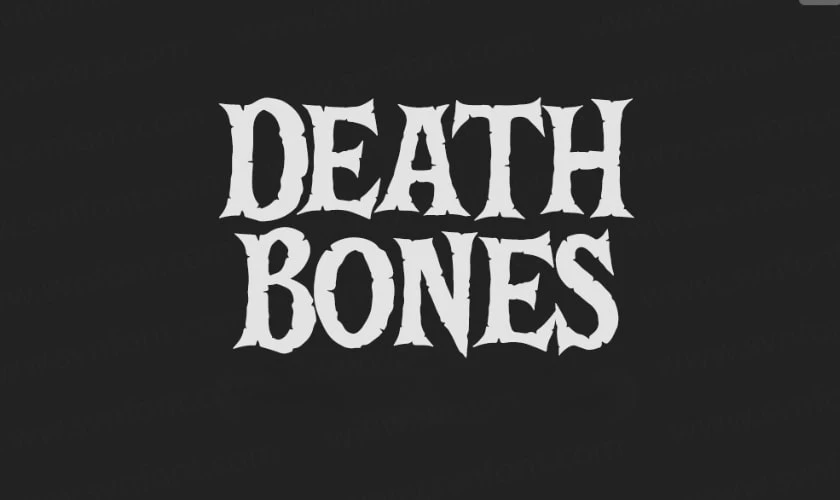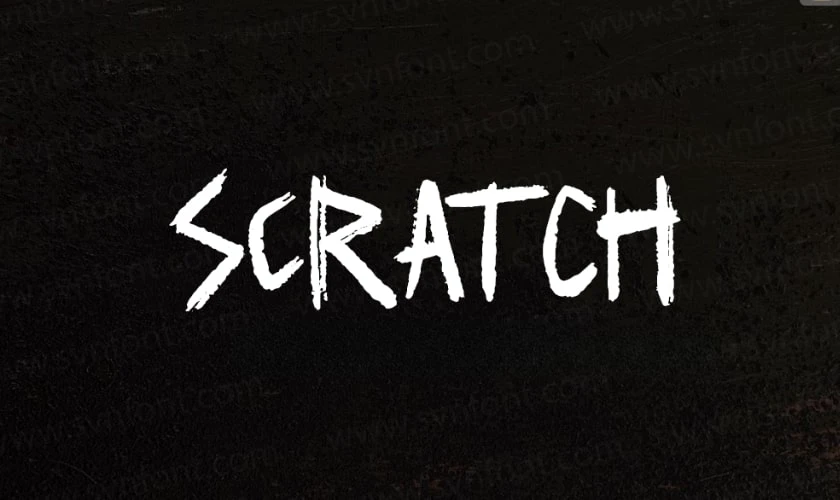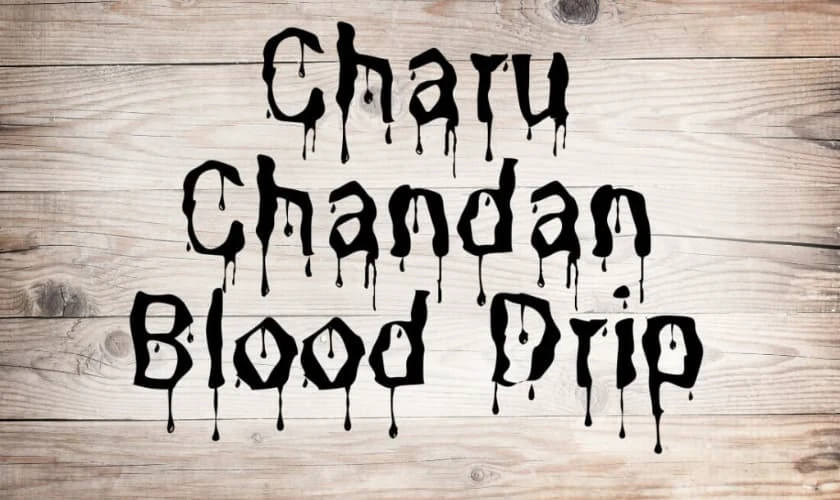
79+ Font Halloween Việt hóa đẹp, độc đáo, miễn phí
Font Halloween là yếu tố quan trọng giúp thiết kế trở nên ấn tượng và mang không khí lễ hội. Với nhiều lựa chọn từ, bạn có thể dễ dàng áp dụng trong poster, banner hoặc thiệp mời. Hãy tham khảo bộ sưu tập font chữ Halloween Việt hóa miễn phí ngay dưới đây để tạo nên sản phẩm sáng tạo, độc đáo và dễ sử dụng.
Tìm kiếm một font Halloween phù hợp sẽ giúp các thiết kế của bạn trở nên ma mị và ấn tượng hơn trong mùa lễ hội này. Với 15 gợi ý font Việt hóa đẹp dưới đây, bạn có thể dễ dàng tạo ra những tác phẩm đậm chất kinh dị, độc đáo.
Font Halloween việt hóa Them Bones mang phong cách xương rợn độc đáo. Đây là lựa chọn tuyệt vời cho các thiết kế poster, banner hoặc tiêu đề chủ đề ma quái. Font có đường nét mạnh mẽ, chi tiết giống xương người giúp chữ trở nên nổi bật. Ưu điểm lớn của font chữ Halloween này là hỗ trợ đầy đủ tiếng Việt, dễ sử dụng và hiển thị rõ ràng.
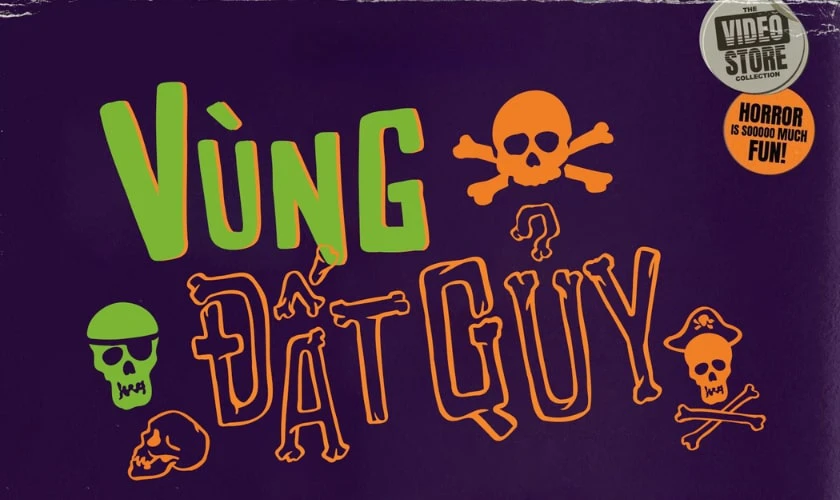
Người thiết kế có thể kết hợp với tông màu tối hoặc cam để tạo không khí Halloween. Khi dùng cho dòng chữ Happy Halloween, font này sẽ gây ấn tượng mạnh và thu hút ánh nhìn. Đây là một trong những font chữ Halloween việt hóa miễn phí được nhiều designer lựa chọn.
1FTV VIP Shlop là một halloween font việt hóa được nhiều designer yêu thích. Font này có đường nét ma mị, kiểu chữ gãy khúc mang cảm giác rùng rợn. Nó phù hợp cho thiết kế tiêu đề, poster sự kiện hoặc các ấn phẩm Halloween. Ưu điểm lớn nhất là font chữ halloween việt hóa này hỗ trợ tiếng Việt đầy đủ, dễ dàng cài đặt trên nhiều phần mềm.
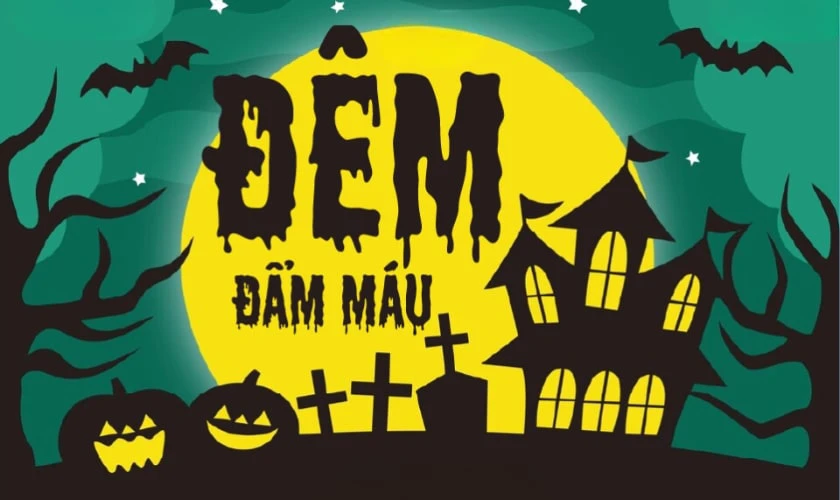
Khi sử dụng trong banner hoặc poster Happy Halloween, font tạo nên phong cách ấn tượng và độc đáo. Người thiết kế có thể kết hợp font với nền đen hoặc cam để làm nổi bật chữ. Đây là một font halloween việt hóa miễn phí, dễ tải và sử dụng ngay.
TH Flavors là một font chữ halloween việt hóa mang phong cách ma mị, độc đáo. Font có đường nét mềm mại nhưng vẫn giữ sự u ám, phù hợp cho thiết kế poster, banner hoặc thiệp Halloween. Đây là font halloween việt hóa hỗ trợ đầy đủ dấu tiếng Việt, dễ dàng sử dụng trên nhiều công cụ.
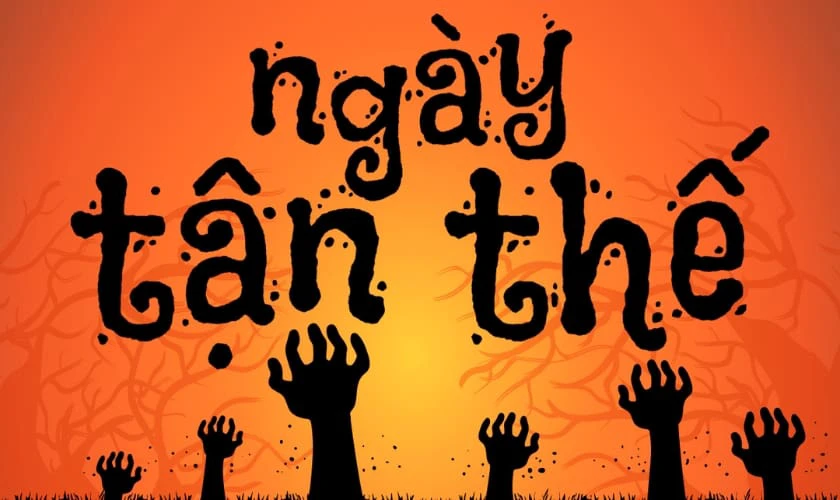
Khi đặt trong tiêu đề Happy Halloween font, chữ sẽ nổi bật với hiệu ứng lạ mắt. Người mới bắt đầu làm thiết kế cũng dễ dàng áp dụng font này mà không gặp khó khăn. Font này giúp tăng tính thẩm mỹ và chuyên nghiệp cho các dự án chủ đề kinh dị.
Sayuri Halloween Island là một halloween font việt hóa được nhiều người yêu thích. Font này mang nét chữ uốn lượn, có chi tiết trang trí nhỏ tạo cảm giác bí ẩn. Đây là lựa chọn phù hợp cho poster, tiêu đề sự kiện hoặc lời chúc Happy Halloween. Font chữ halloween việt hóa này hỗ trợ đầy đủ dấu tiếng Việt nên bạn dễ dàng sử dụng.
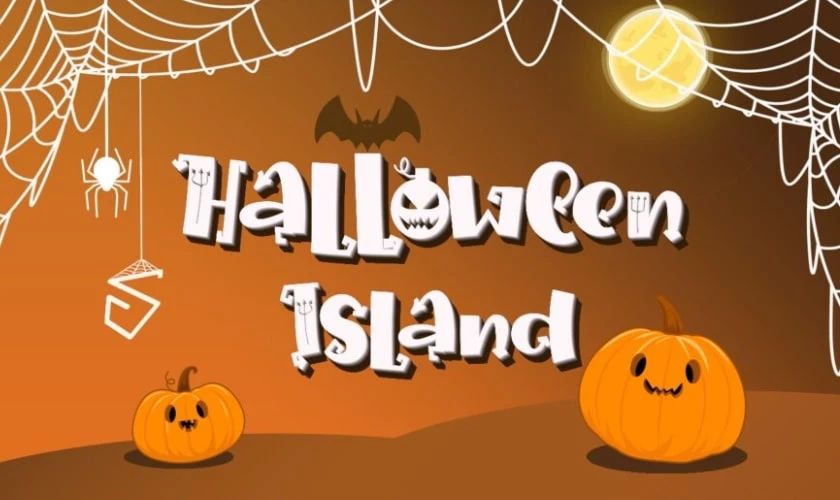
Khi kết hợp với nền màu cam, tím hoặc đen, chữ sẽ nổi bật và thu hút ánh nhìn. Người thiết kế có thể áp dụng font này cho banner, thiệp hoặc các sản phẩm in ấn Halloween. Font miễn phí và dễ tải về để sử dụng ngay.
1FTV Spider Home là một font halloween việt hóa mang phong cách tơ nhện độc đáo. Font này được nhiều designer sử dụng để tạo không gian rùng rợn cho thiết kế. Nét chữ góc cạnh, kèm theo chi tiết như dây nhện, giúp font trở nên đặc biệt.
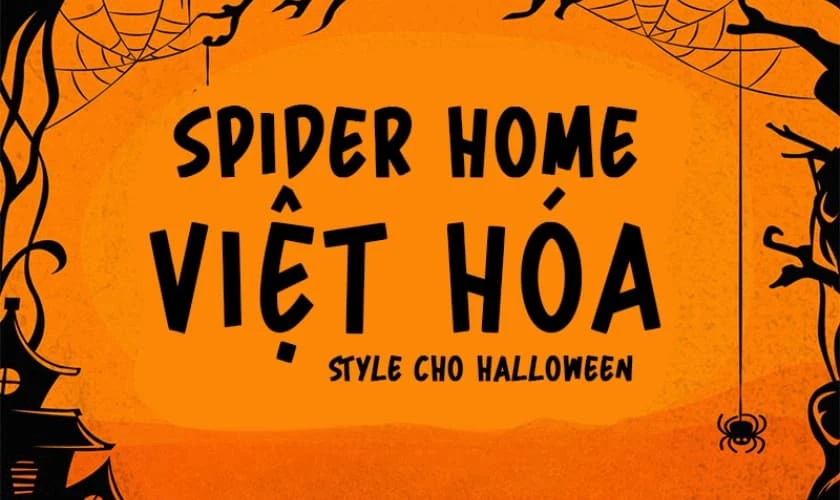
Khi sử dụng trong tiêu đề poster hoặc banner Halloween, font chữ halloween này dễ dàng gây ấn tượng mạnh. Đây là font chữ halloween việt hóa đầy đủ dấu tiếng Việt nên phù hợp cho nhiều dự án. Người dùng mới có thể áp dụng dễ dàng trong thiết kế poster “Happy Halloween”. Font miễn phí, dễ tải và cài đặt nhanh chóng.
1FTV VIP Ghoulies là một font halloween việt hóa mang phong cách kinh dị rõ rệt. Font có nét chữ răng cưa, méo mó tạo cảm giác ma quái. Đây là lựa chọn phù hợp cho các thiết kế poster, banner hoặc tiêu đề Halloween. Ưu điểm lớn của font chữ halloween việt hóa này là hỗ trợ tiếng Việt đầy đủ, dễ dàng sử dụng trên mọi phần mềm.
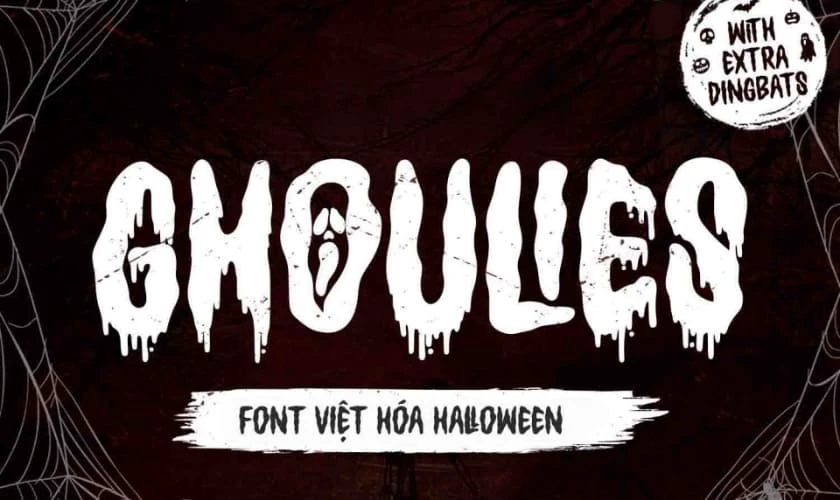
Khi kết hợp với tông màu đỏ hoặc cam, chữ sẽ nổi bật trên nền đen huyền bí. Font này phù hợp với những ai muốn thiết kế poster Happy Halloween ấn tượng, rùng rợn và dễ đọc. Đây là một font halloween miễn phí, dễ tải và áp dụng ngay.
TH Jengled là một halloween font việt hóa rất đặc biệt với nét chữ rách nát và đường cắt mạnh mẽ. Font này mang lại cảm giác rùng rợn, phù hợp cho thiết kế banner, poster hoặc poster phim kinh dị.
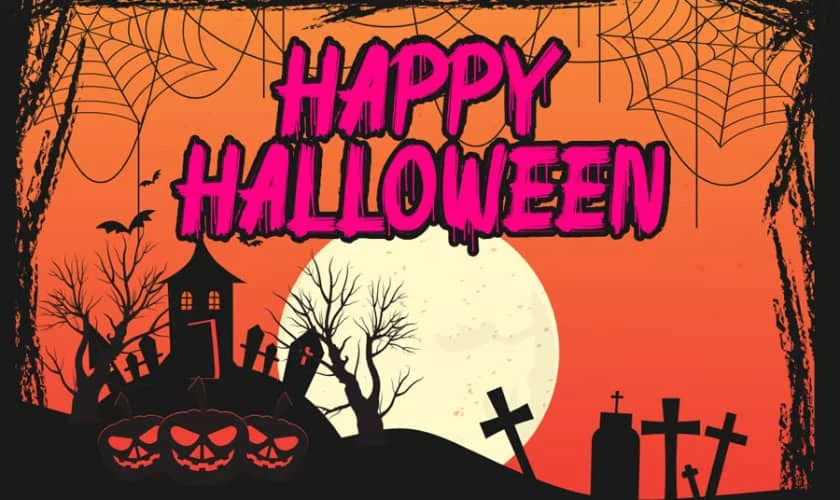
Đây là một font chữ halloween việt hóa hỗ trợ đầy đủ tiếng Việt nên dễ dàng áp dụng. Khi sử dụng trong thiết kế Happy Halloween, chữ sẽ nổi bật và tạo ấn tượng ma mị ngay lập tức. Người thiết kế có thể dùng font này với nền màu tối để tăng hiệu ứng thị giác. Đây là font miễn phí, cài đặt nhanh, giúp bạn tiết kiệm thời gian.